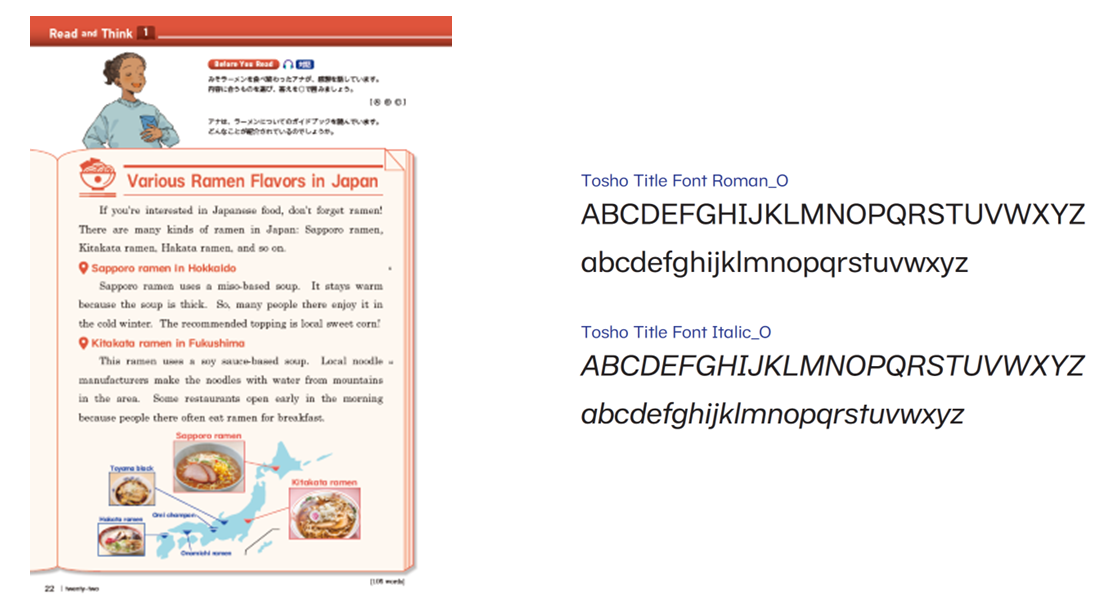
モリサワと教科書出版大手・東京書籍がオリジナル欧文フォント(通称:Tosho Title Font)を共同開発して令和7年度版中学校英語教科書に採用
モリサワは、東京書籍のオリジナル欧文フォント(通称:Tosho Title Font)を共同開発し、令和7年度版の中学校英語教科書「NEW HORIZON」に採用されたことを2024年4月23日に発表した。
近年では、より多くの児童、生徒が学びやすいよう、教科書で使用するフォントなどへの配慮が進んでいる。
東京書籍では、英語教育の中で生徒が判別しにくい文字を調査し、「読み書きでつまずく生徒をゼロにしたい」という思いのもと、Tosho Title Fontを開発。
具体的には、「o」「c」「e」など、形の似た文字の読み間違いを防ぐため、空きを広げたり、太さを調整したりするなど工夫している。
また、従来利用していたフォントの課題であったスペーシングや記号類も一新し、全体を通して一貫したデザインに仕上げた。
Tosho Title Fontは文字の判別性を重視しながらも、日本語と組み合わせた際にも違和感がないデザインとなっている。
令和7年版の中学校英語教科書NEW HORIZONに採用され、今後も東京書籍の教材を中心に幅広く利用される予定となる。
▼中学校英語教科書NEW HORIZONのタイトルや小見出し、図表の中で使われています(左) オリジナル欧文フォント書体見本(右)